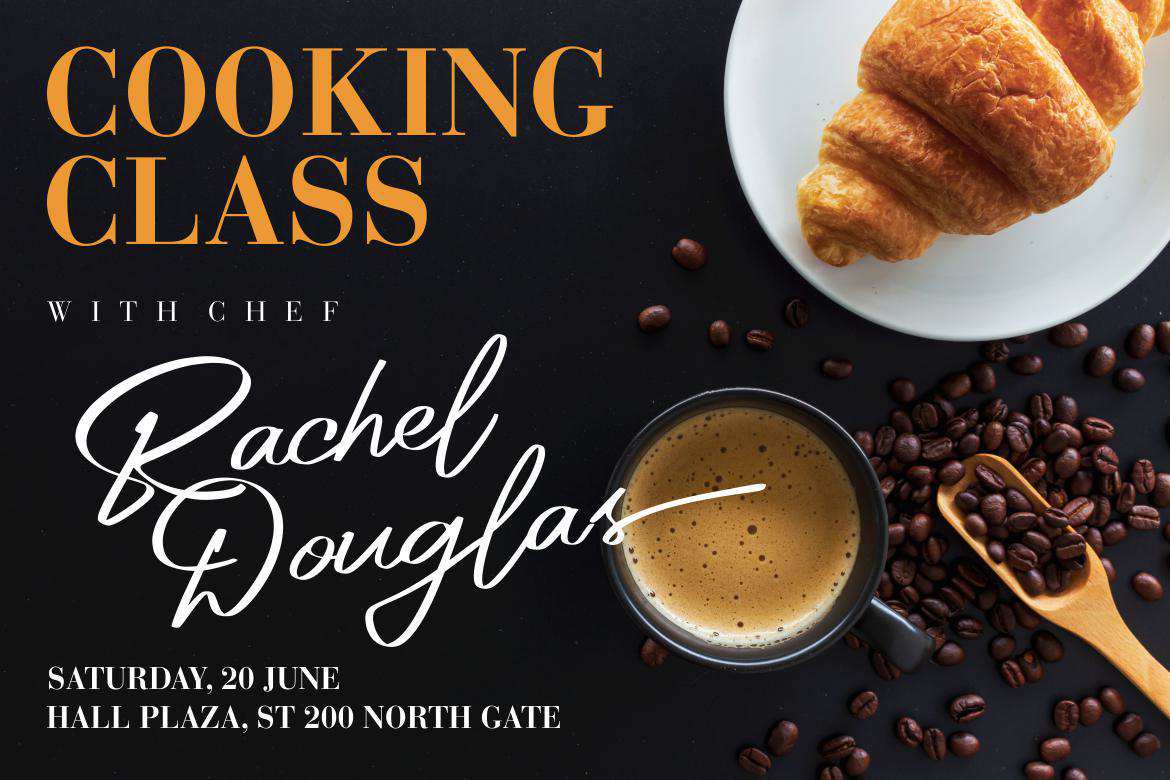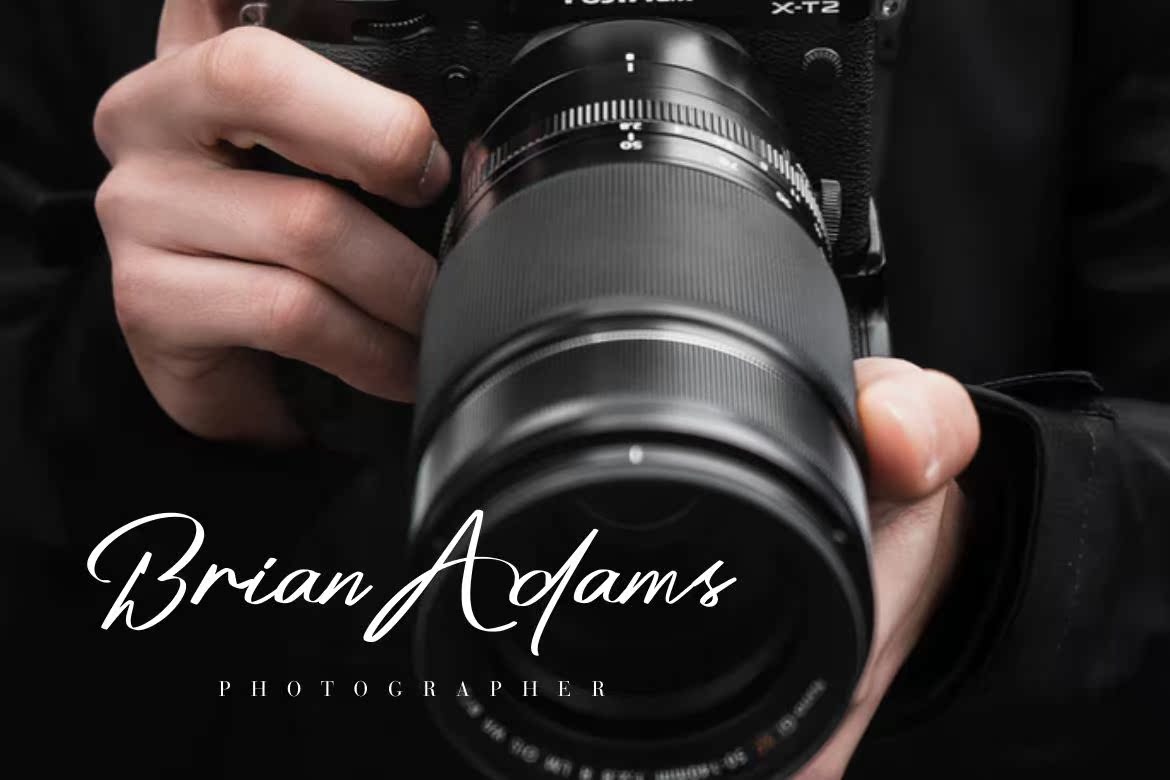
PlatinumSignature Fonts是一种传统的手工签名,而不是手工制作的天然毛刷。该Fonts非常适合为您的照片、图片、打印模板、海报、品牌、报价或任何内容创建签名或水印。可选和Swash特征都是可用的。但是,如果您使用Adobe/CorelDraw,您只需将其中一个字母/数字(用于清洗)和一个窄字符显示在字母下,您可以用其他字符替换。PlatinumSignature Fonts是一种传统的手写体,而不是手工制作的自然画笔。该Fonts非常适合为您的照片或打印模板、海报、品牌、报价、,或任何内容。可选字符和Swash字符都是可用的。但是,如果使用Adobe/CorelDraw,您只需将其中一个字母/数字(用于清洗)阻塞并缩小,就可以将其替换为可选字符。